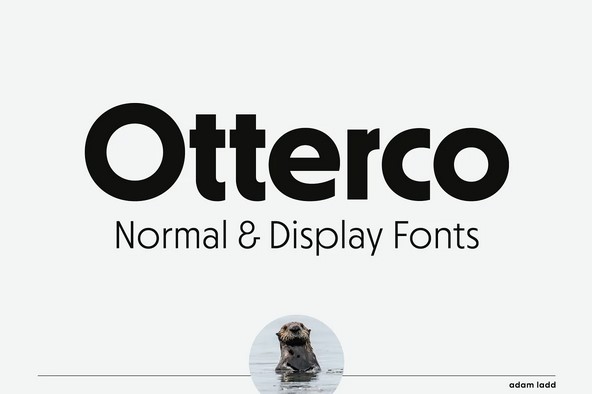
Creativemarket Otterco Font 2021
[Creativemarket] Otterco Font (2021)
Otterco - это семейство геометрических шрифтов без засечек с разнообразными круглыми и узкими символами. Сочетая в себе оттенок ретро и современные качества, этот шрифт чистый и нейтральный, но не скучный. Это профессиональный, но в то же время уникальный и веселый шрифт. Контраст в ширине символов создает четкий визуальный ритм, а терминалы вертикального среза сохраняют его последовательность, силу и резкость. Сконструированный с большой х-высотой и низким контрастом хода, он может подходить для различных применений.
Шрифты, входящие как в семейство Normal, так и в семейство Display, могут быть использованы для еще большего количества настроек и тональности голоса. Нормальный дизайн имеет немного меньший контраст между символами по ширине и меньшее количество пробела, что удобно как для маленького, так и для большого текста. В то время как конструкция Дисплея имеет больший контраст по ширине символов и меньшие пробелы - хорошо для текста большого размера, который привлекает внимание.
Благодаря 32 шрифтам, выполненным тонким сквозным шрифтом с дополнительным жирным шрифтом (плюс курсив), Otterco прекрасно подходит как в качестве универсального текста, так и в качестве шрифта для брендинга, рекламы, упаковки, заголовков, журналов, веб-сайтов, дизайна логотипов и многого другого.